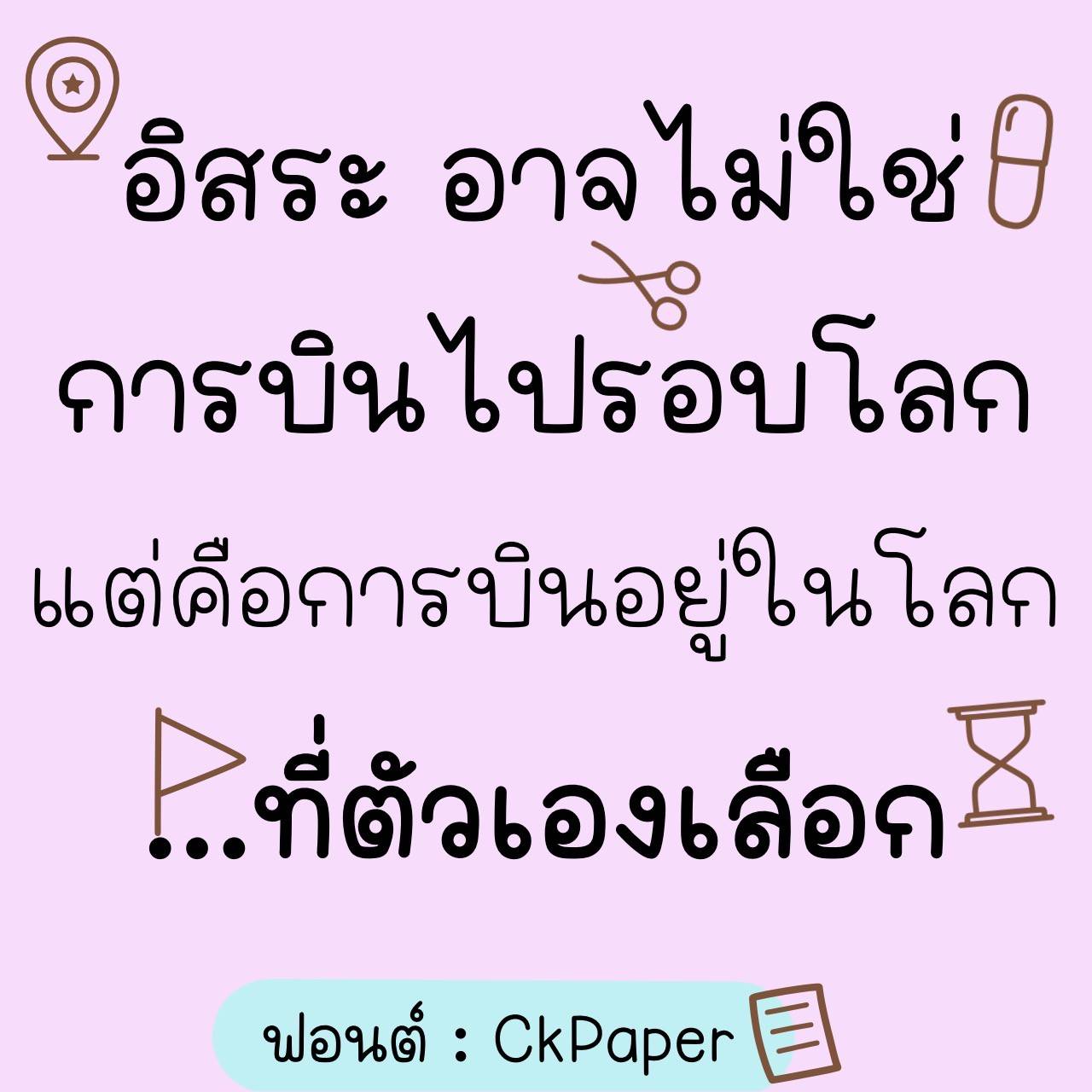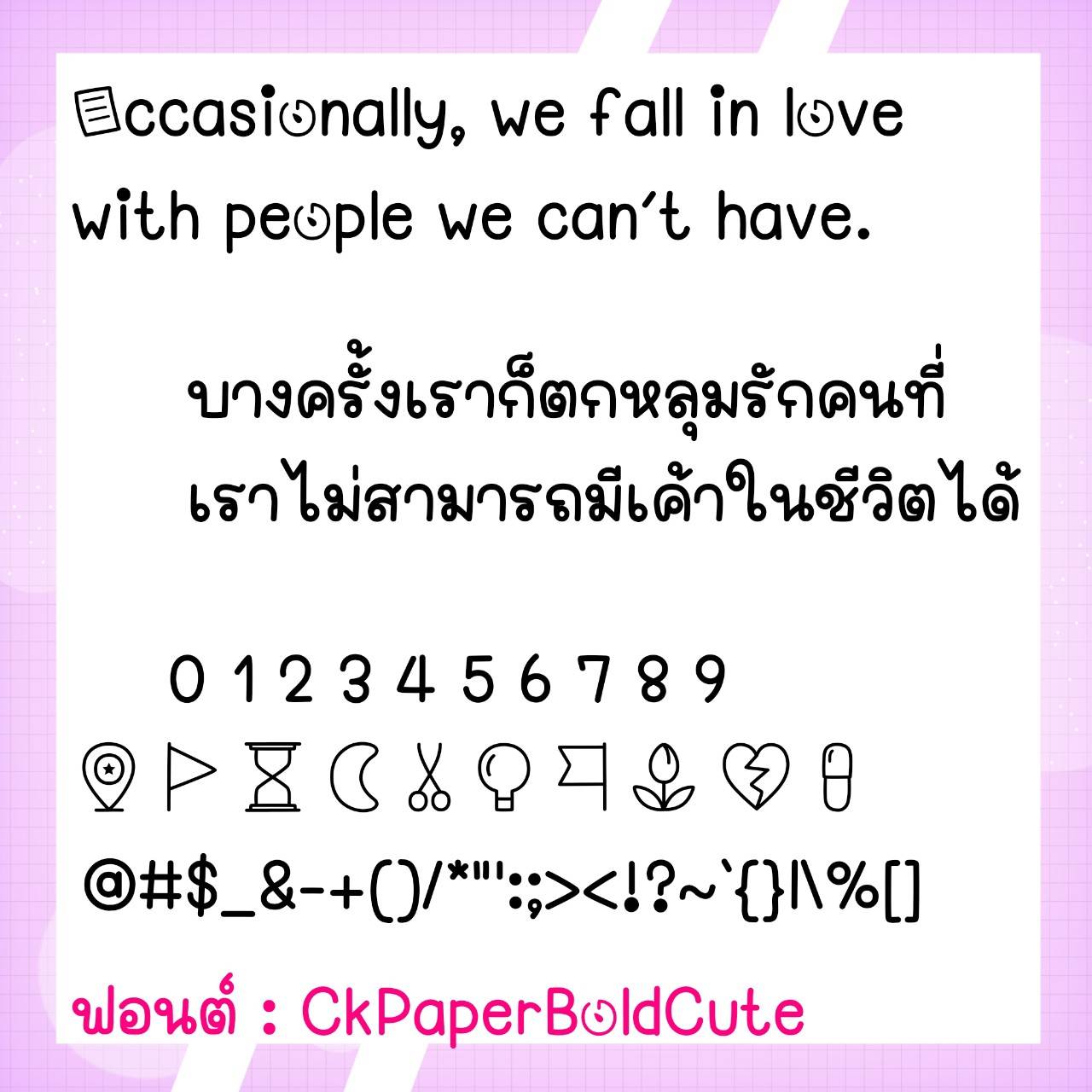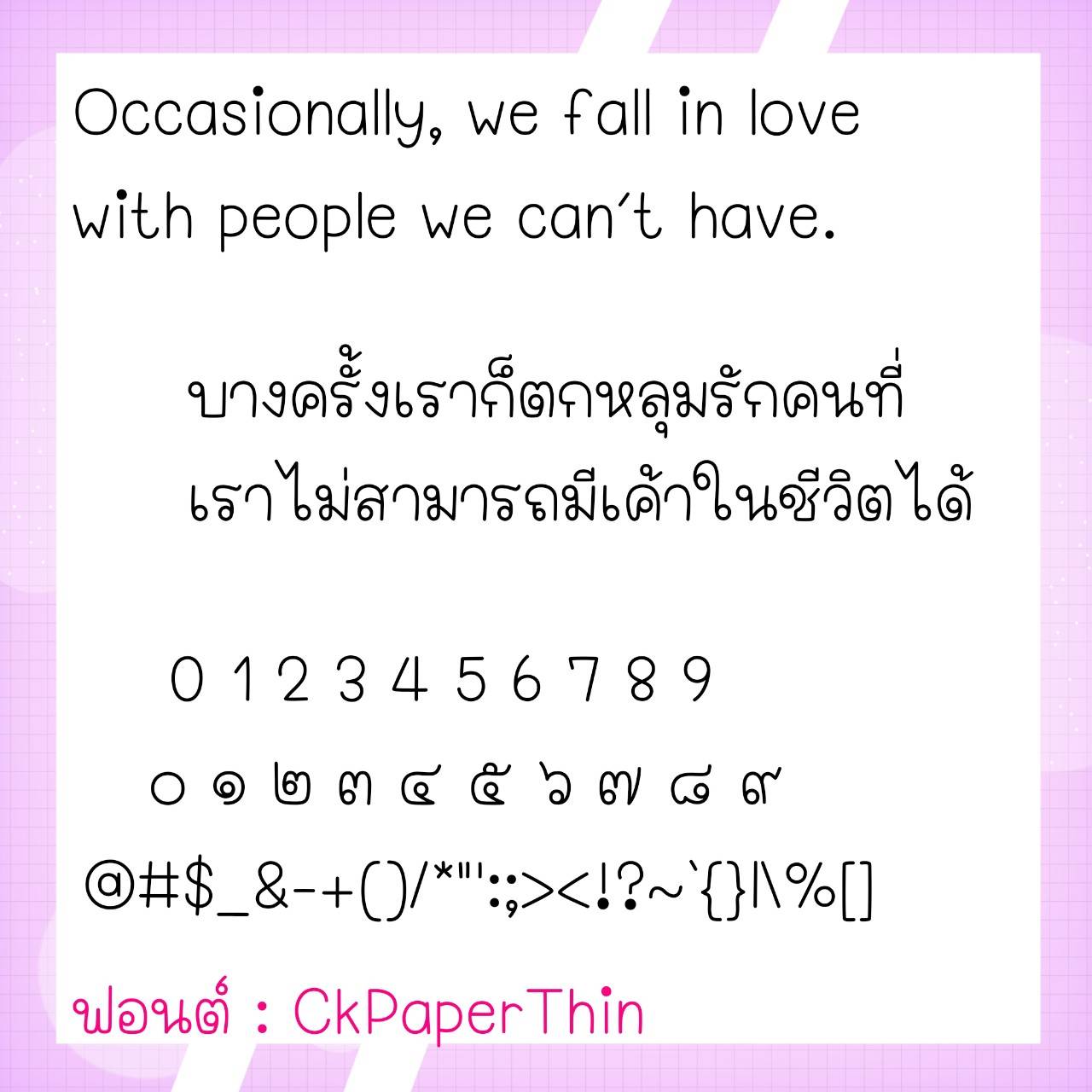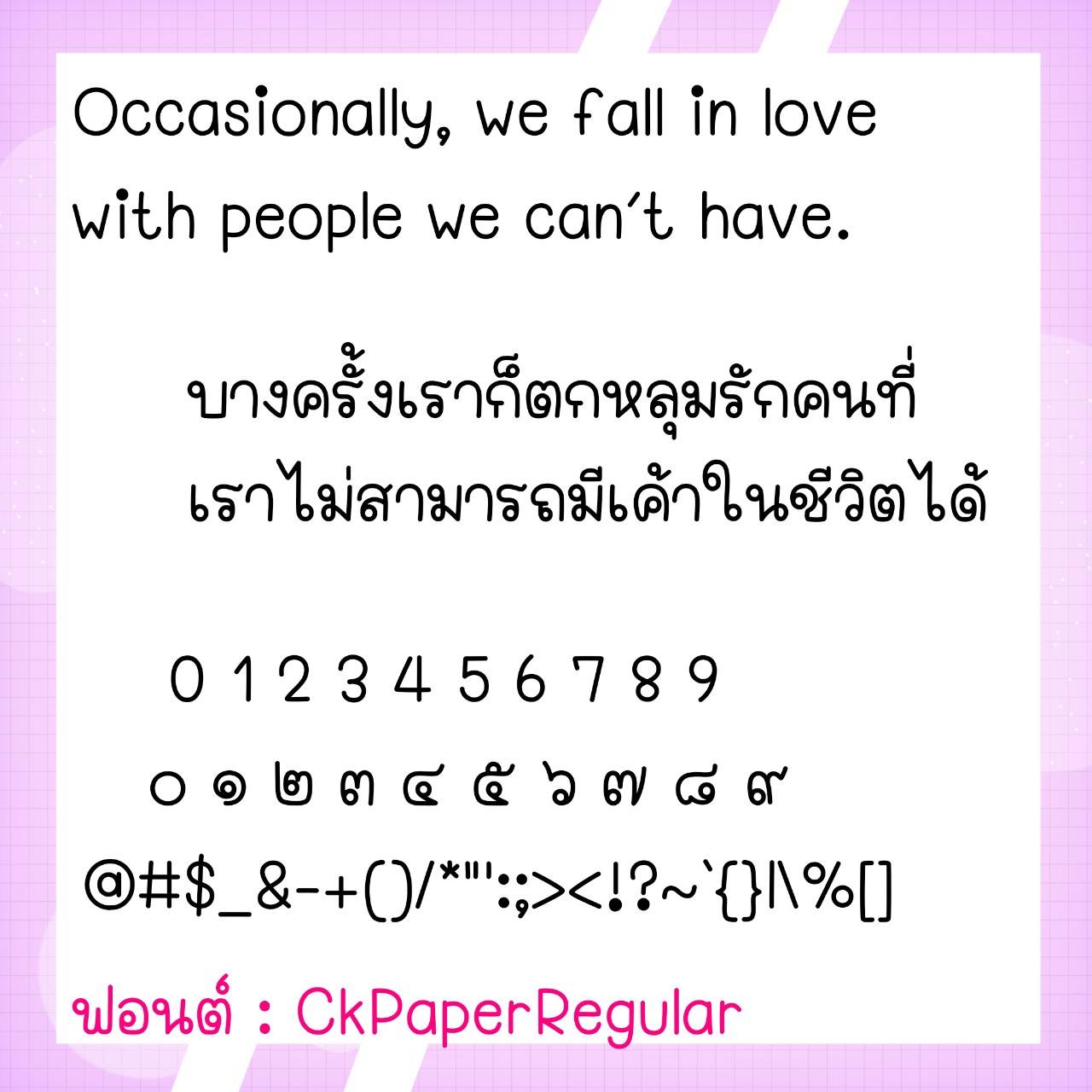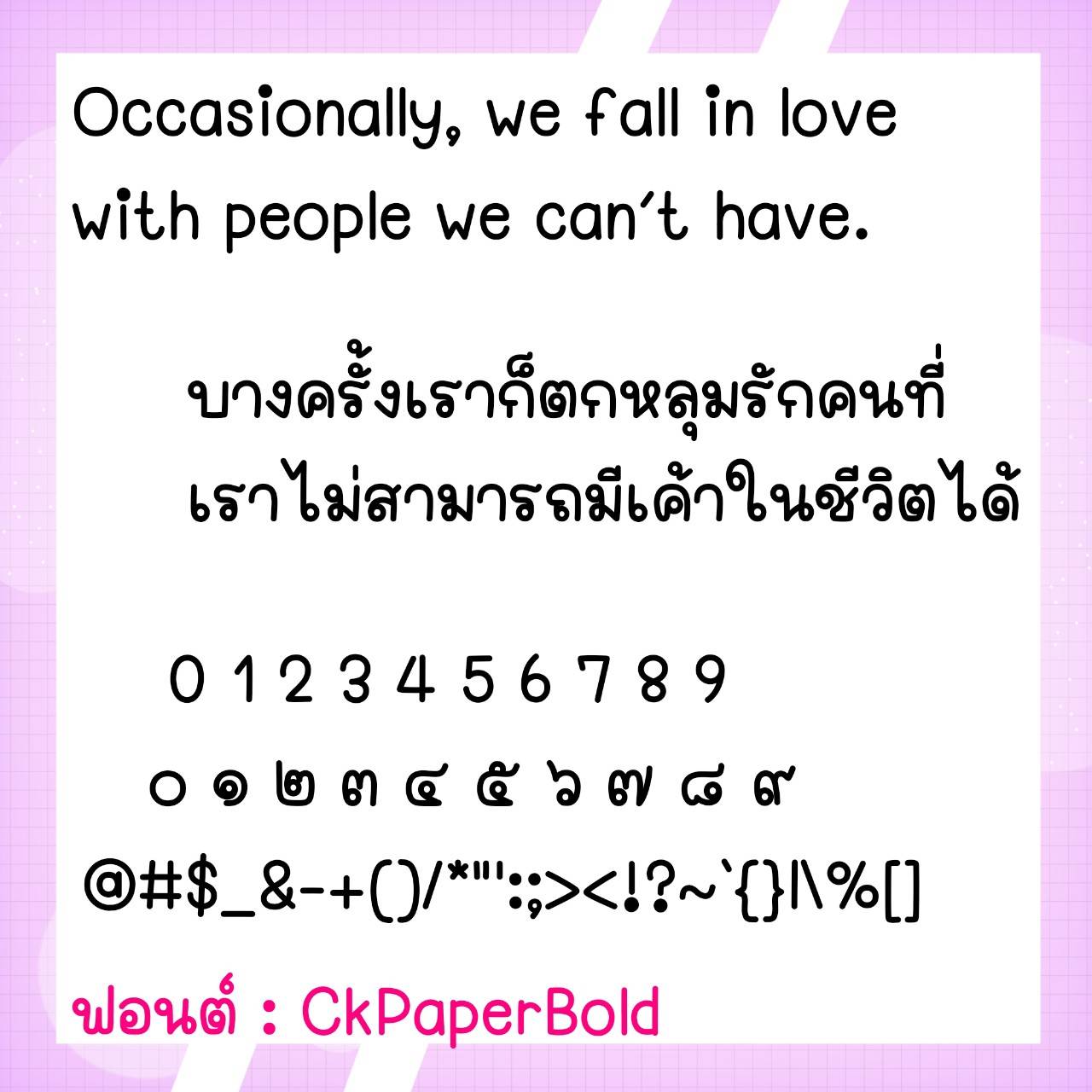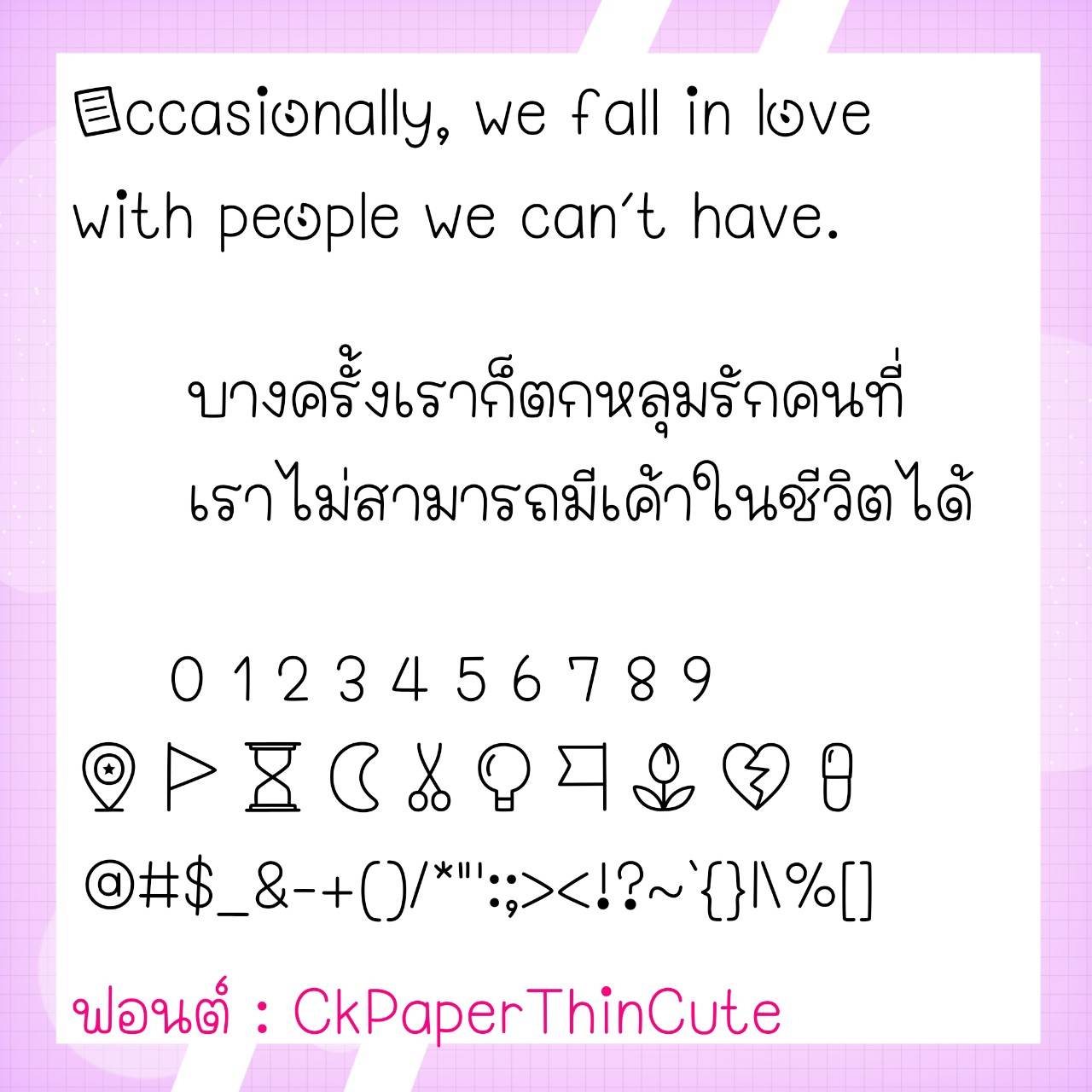
Font CkPaper
ชื่อสินค้า : Font CkPaper 💙
🔸 ฟอนต์ลายมือตัวอวบอ้วน มีความกึ่งเหลี่ยมกึ่งมนคละกันไป เป็นฟอนต์ที่ดูน่ารักปุ๊กปิ๊ก เหมาะกับการใช้งานได้หลากหลาย และยังมีไฟล์อิโมจิน่ารักๆ ที่ใช้ปืนเลขไทยให้ด้วยค่ะ 🥰💙
🔹 A chubby handwritten font with a mix of semi-angular and semi-rounded shapes. It is a cute and adorable font that is suitable for a variety of uses. It also has a cute emoji file that uses Thai numerals. 🥰💙